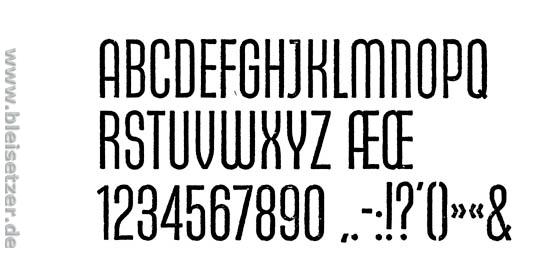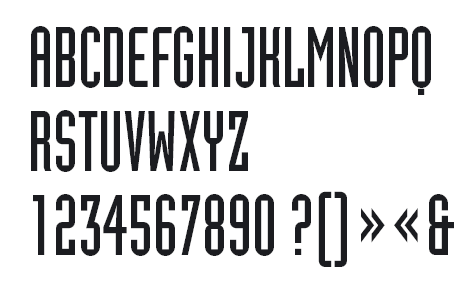
suche was spezielles
ich suche nach einer schrift bei der die "außenbalken" des Ws senkrecht sind. also etwa so I/\I... naja.
konnte bisher keine passende schrift finden. vielleicht fällt ja jemandem eine ein. es sollte möglicht eine sans sein.
senkrechtes w oft bei der fraktur, ansonsten:
so richtig schön sind die ja nicht unbedingt...
tip: "zeichne" dir ein senkrechtes w, speichere als jpg und suche über: https://www.myfonts.com/WhatTheFont/
da kommen etliche schriften, kann dir den link jedoch nicht senden
Ne, die Industria unterscheidet sich schon merklich. Ich hatte mir ja mal bei typophile gewünscht, dass sich jemand an die Digitalisierung der Maximum A heranmacht. Wer weiss, vielleicht existiert ja eine Digitalisierung schon, irgendwo in den Weiten des …